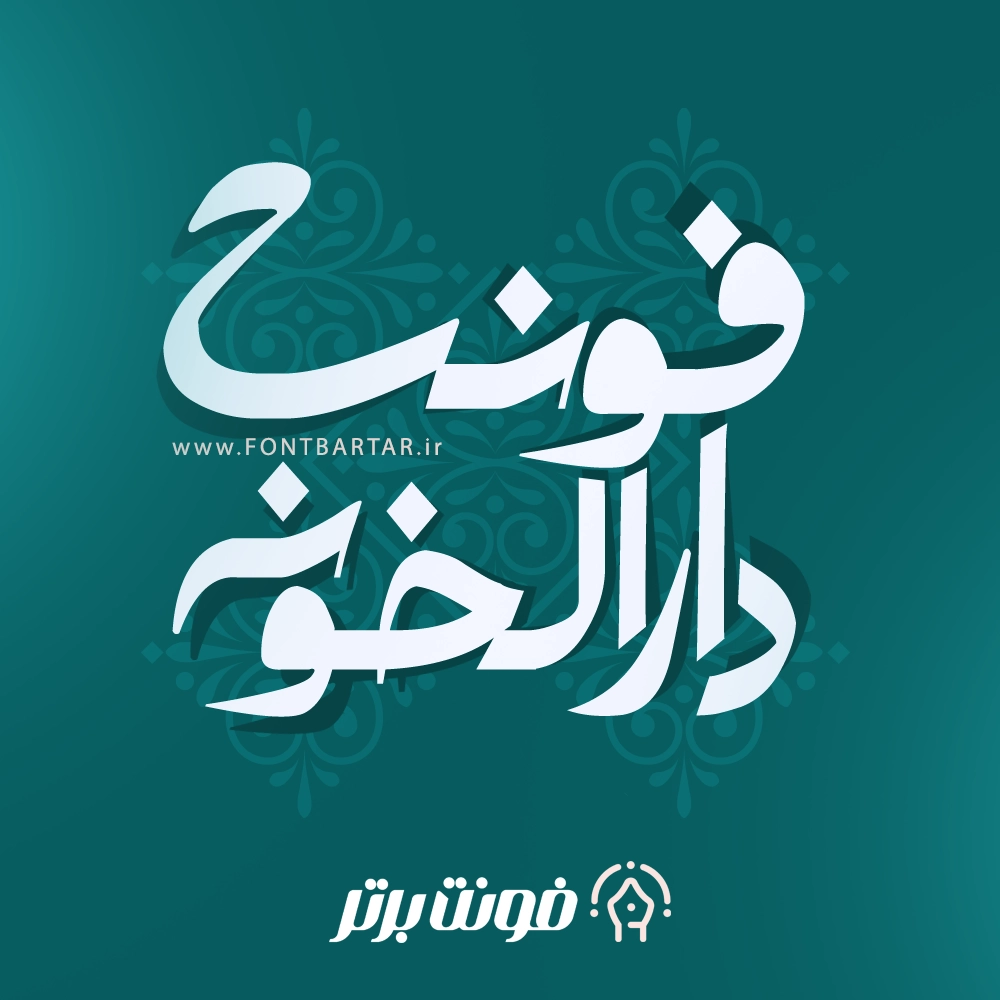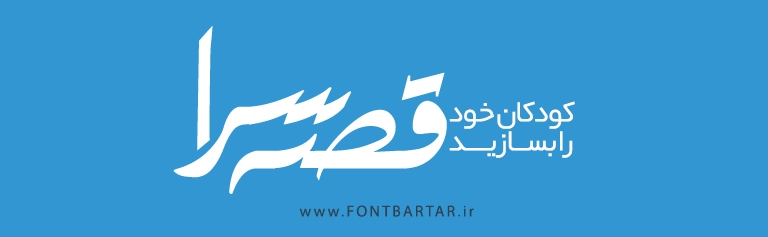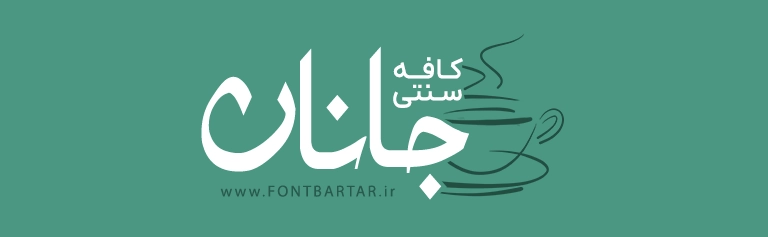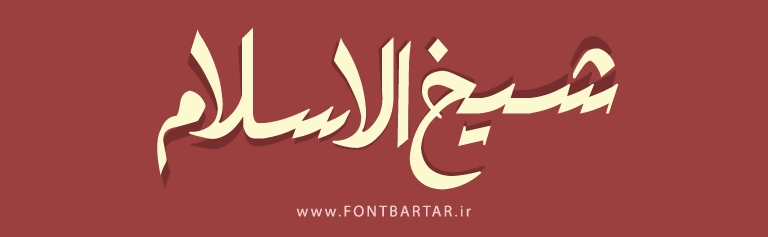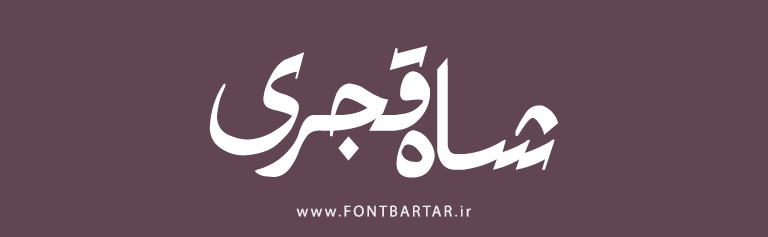
فونت جدید دارالخونه
Daralkhone Font
فونت نوستالژی دارالخونه
دانلود فونت فارسی اگر به دنبال یک فونت فارسی جدید، زیبا و خاص برای طراحی‌های خود هستید، فونت دارالخونه می‌تواند بهترین انتخاب شما باشد. فونت جدید دارالخونه حرفه‌ای با الهام از سبک‌های سنتی ایرانی و ترکیب آن با مدرن‌ترین المان‌های طراحی گرافیکی ساخته شده است و برای طراحان گرافیک، تولیدکنندگان محتوا، تایپوگرافی و طراحی لوگو انتخابی بی‌نظیر است.
ویژگی‌ های فونت نوستالژی دارالخونه:
• مناسب برای طراحی پوستر، کارت ویزیت، بنر تبلیغاتی و لوگوتایپ
• استایل شیک و خوانایی بالا در متن‌های طولانی و کوتاه
چرا فونت دارالخونه حس نوستالژی دارد؟
خیلی وقت‌ها در طراحی نیاز داریم علاوه بر زیبایی بصری، احساسات کاربر را تحریک کنیم. فونت دانلود فونت دارالخونه با حال‌وهوای قدیمی خود، حس خاطره و نوستالژی را تداعی می‌کند. وقتی کاربر متنی را با این فونت می‌خواند، به یاد تابلوهای قدیمی شهر، پوسترهای فرهنگی و حتی کتاب‌های درسی گذشته می‌افتد. همین ویژگی باعث می‌شود طراحی شما متفاوت، احساسی و ماندگار شود.
کاربردهای فونت دارالخونه
• طراحی لوگوهای خاص با هویت ایرانی
• تایپوگرافی و پوسترهای فرهنگی و هنری
• جلد کتاب و مجله با حس نوستالژی
• طراحی بنر تبلیغاتی و شبکه‌های اجتماعی
• استفاده در برندینگ برای نمایش اصالت و اعتماد